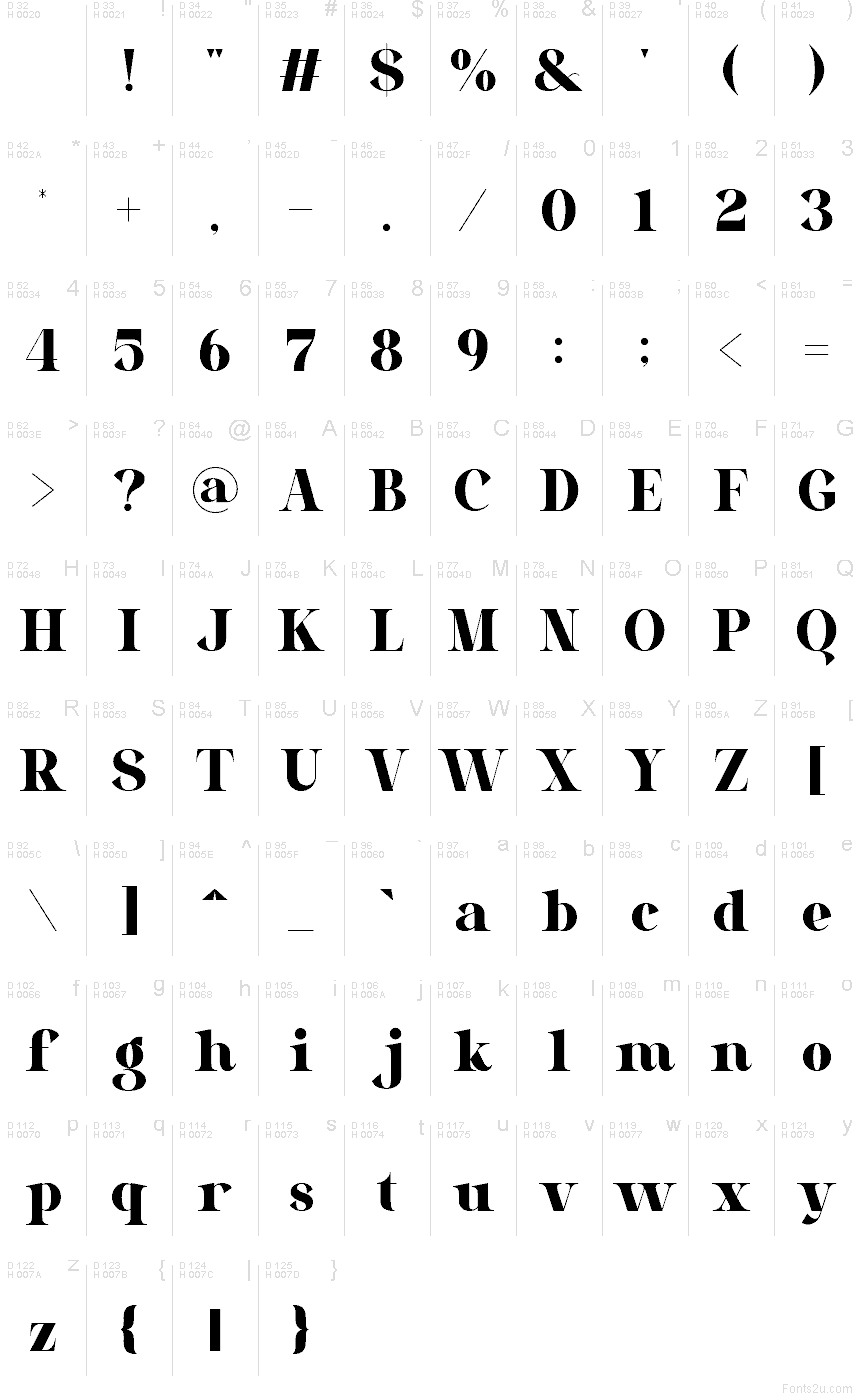
Naolen, da Ermedia Studio, é uma fonte serifada gratuita de alto contraste, com proporções imponentes voltadas para o universo da moda e uma silhueta excepcionalmente nítida. Junções ultrafinas tornam seus largos traços verticais ainda mais incisivos.
O estilo didone a insere naturalmente em publicações de moda e embalagens de luxo, onde as variações acentuadas no traço combinam com uma linguagem visual refinada. Cartazes culturais e o branding de perfumes podem se valer dessa mesma intensidade formal. Ela se mostra mais convincente quando um título exige a autoridade da tipografia editorial clássica e glamourosa.